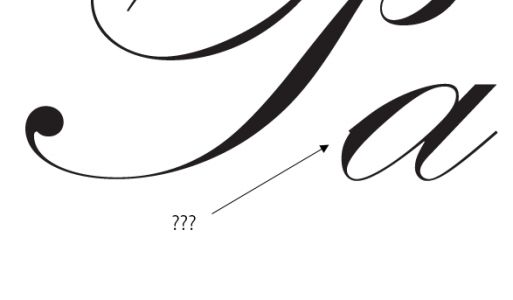
Welche "Schreibschrift" ist das? Bild beigefügt.
Weiß jemand, welche Schriftart das ist? Bitte dringend um Hilfe! (Der Haken am Ende der Schrift gehört schon zum nächsten Buchstaben)
Danke, sieht gut aus, aber was mache ich mit diesen Überhängen? kann ich die ausschalten? 1073_welcheschrift_2.jpg
Da es sich bei beiden nicht um Optenype-Fonts handelt:
nur, wenn eine zweite Schrift ohne die "Überhänge" verfügbar ist, die du stattdessen verwenden kannst (also ein Zeichensatz mit Überhängen, einer ohne, die kombiniert verwendet werden müssen).
Wenn es das auch nicht gibt, ist die Schrift schlichtweg unsauber gestaltet (im Falle von Truetype und Type1 ist es leider auch gar nicht anders möglich).
es gibt diese Schrift hier bei mir nur noch in bold...das war es
und das ganze sieht dann so aus:
ALSO DER TOTALE HORROR
und das Logo muß heute fertig sein...
jemand eine Idee?
Es ist zwar jetzt wohl schon zu spät, aber auch ich schließe mich den vorhergegangenen Aussagen an. Gerade für ein Logo würde ich es in Illustrator/Freehand spationieren. Danach in Pfade umwandeln und die störenden Stellen entfernen – ist natürlich etwas Arbeit, aber ein Logo sollte Dir das wert sein :wink: